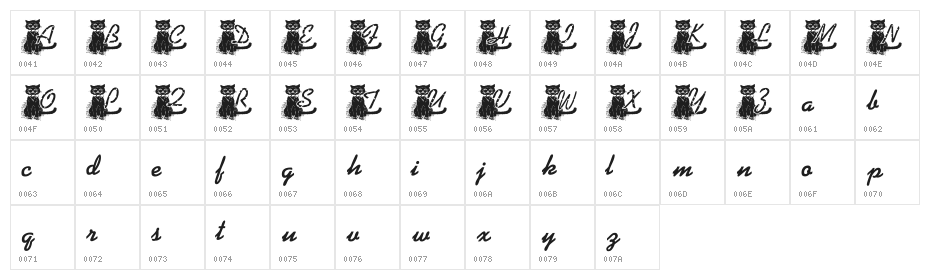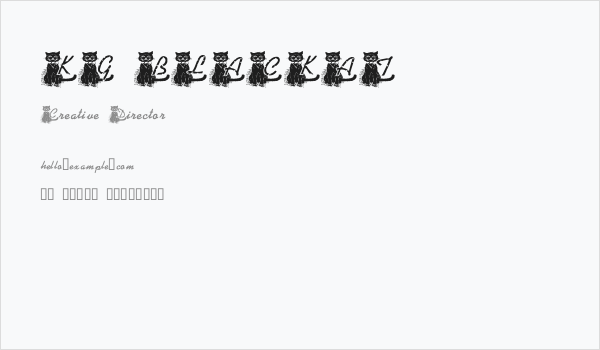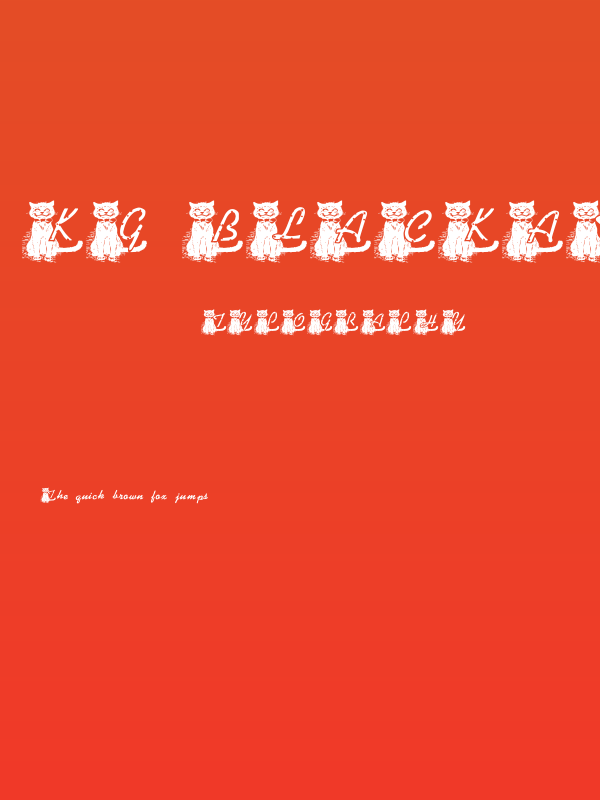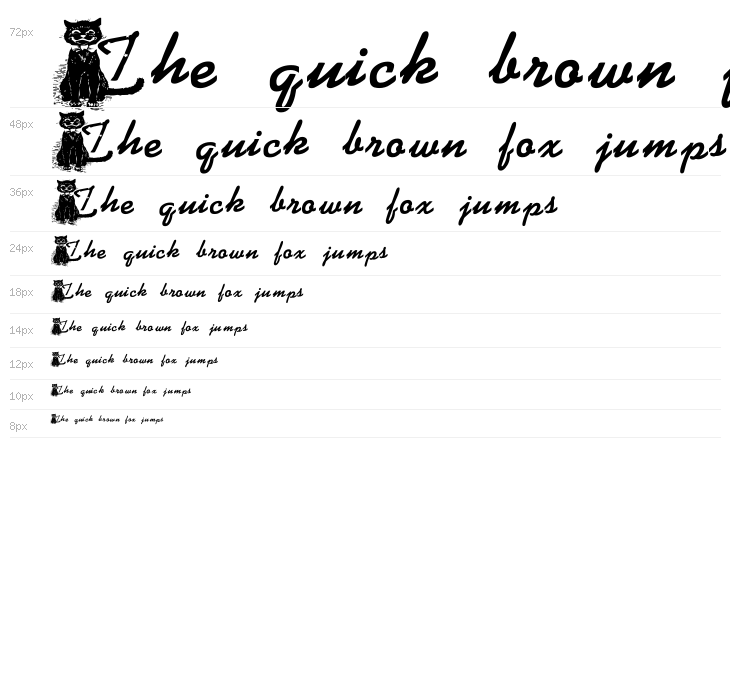
KG BLACKAT Font
| Stile generale | Whimsical |
| Caso d'uso | Logos, Decorative text |
| Progetti proposti | Perfect for children's book covers, playful greeting cards, and whimsical branding projects. |